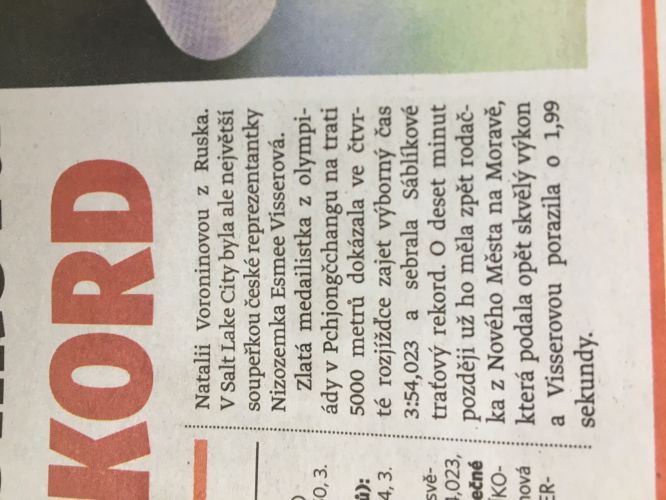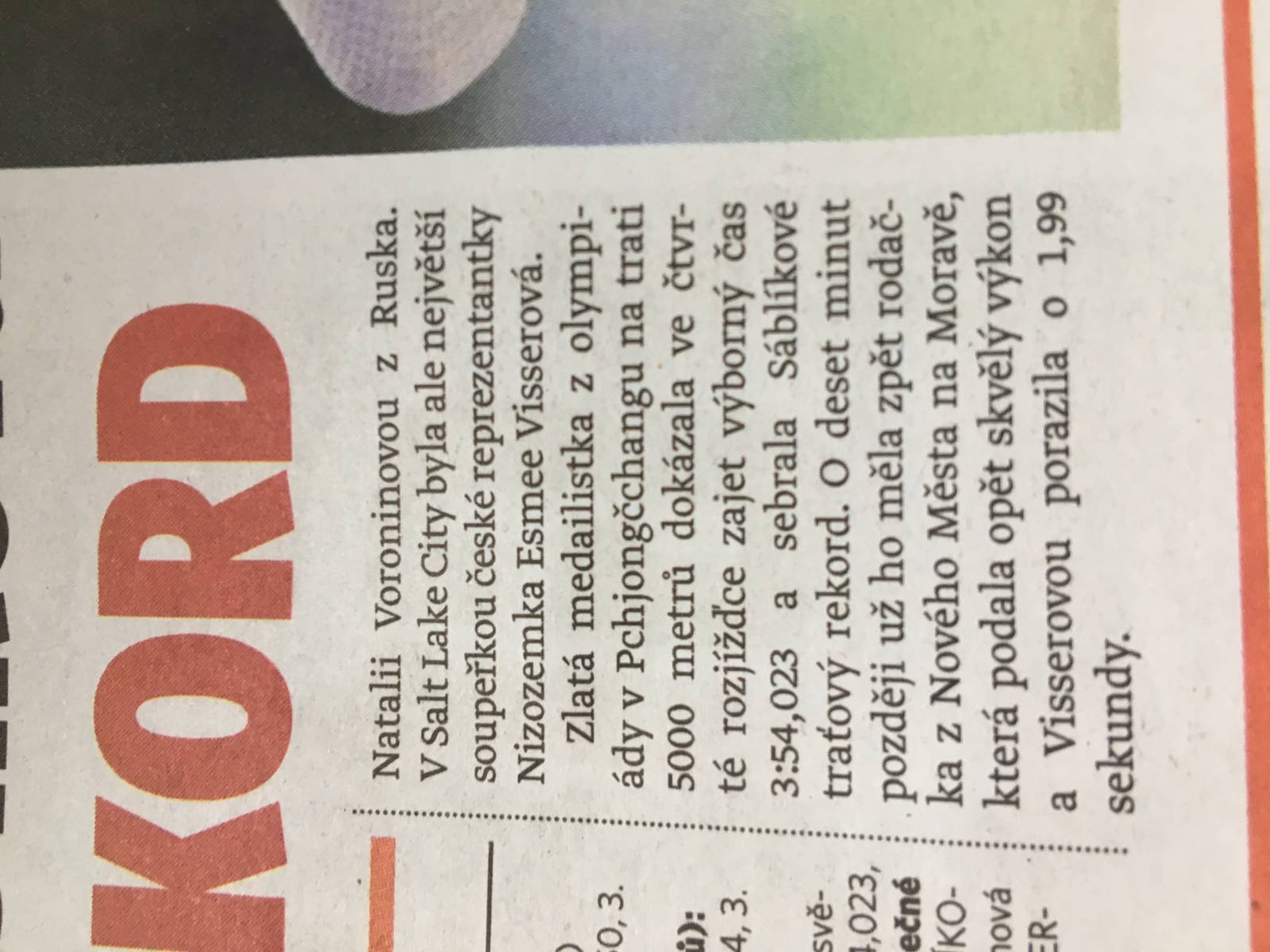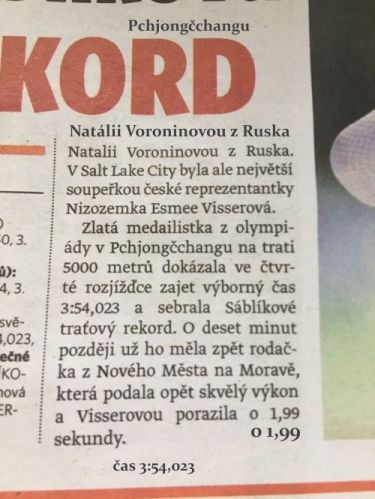
Font písma - Deník Sport
Ahoj, nevite nekdo prosim, jaky font pouziva Denik Sport? Tech fontu ma nespocet, ale myslim tento (viz foto). Diky moc!
Dobrý den. Nemohl by to být font Cambria?
Zdravím, určitě ne, také mě to napadlo, ale všimněte si tiskacího "J" nebo například "y". U "y" tam není ta patka dole :).
Kdysi jsem ho taky hledal, myslím, Constantia, zkus.
Do té doby než začnete psát čísla to vypadá. Čislice již nikoliv.